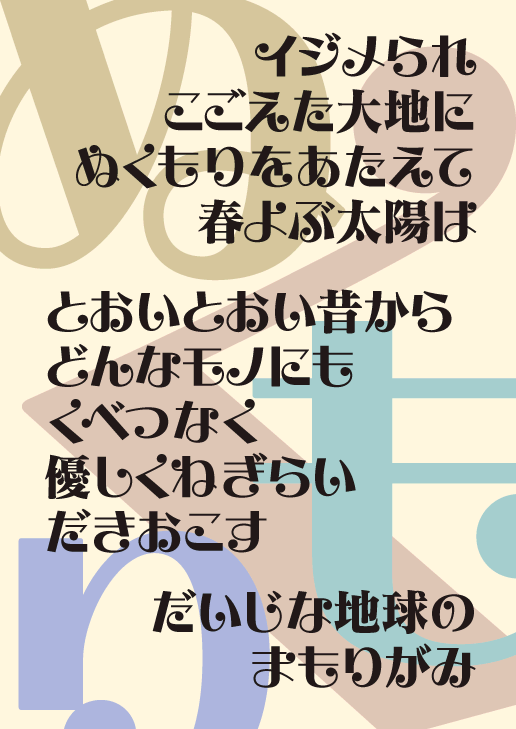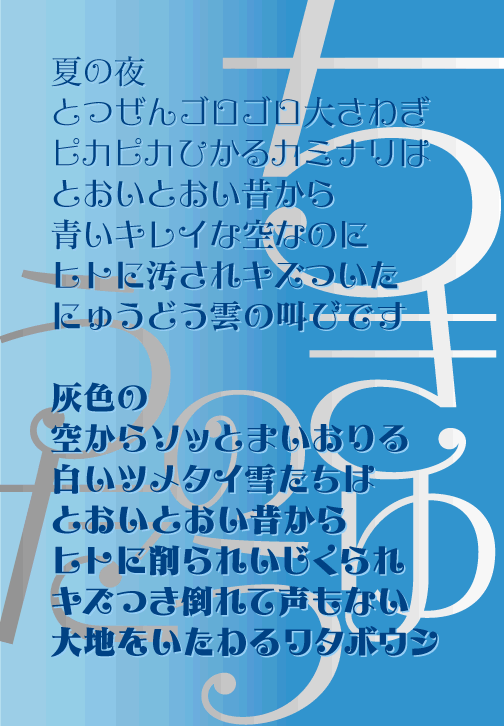
デザイン かな文字の一部にクルンとした丸いアクセントがついた、楽しい書体です。
しかし、その可愛いアクセントも大量に目にするとウルサク感じられてしまいます。
長い文章に使うのは避けて、タイトルなど目立つところに使うと効果的でしょう。
連想されるイメージ
寄せられたコメントから抜粋
レトロチック・耽美・エレガントそのもの・カワイイ・大正モダン・昔のファッション雑誌・おしゃれ・お姫さまちっく・おもしろい・ベルサイユのバラ・70年代・ゴージャス・キレイ・楽しい・魔女っ子メグちゃん・女の子向け・らぶりぃ・ノスタルジック・宝塚みたい・少女漫画・ファンシーショップ・ロマンチック・ケーキ屋・キュート・ハイカラ・乙女チック・くるくる…。